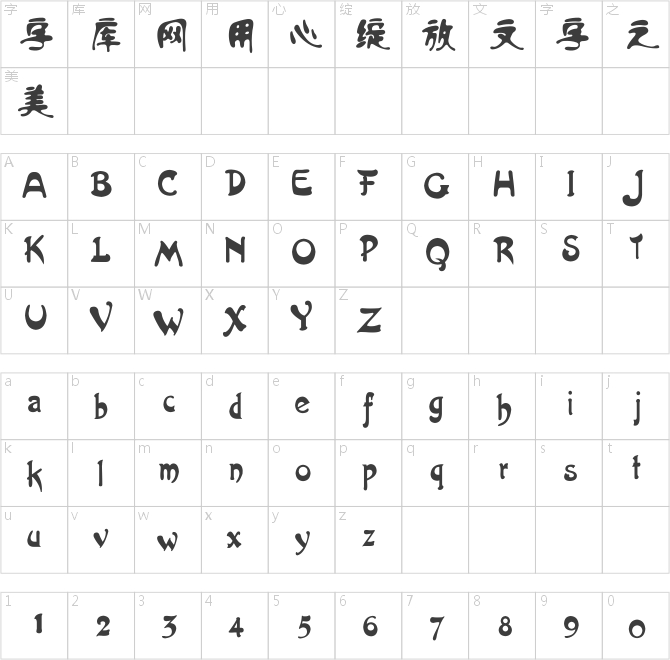
方正流行體簡(jiǎn)體
方正流行體簡(jiǎn)體字體字庫(kù)是一款讓人賞心悅目、百看不厭的中文字體,適合各類廣告和產(chǎn)品包裝設(shè)計(jì)應(yīng)用,字體大小3.29MB,格式為ttf字體,上傳用戶是17199970014,作者/版權(quán)方為方正字庫(kù)